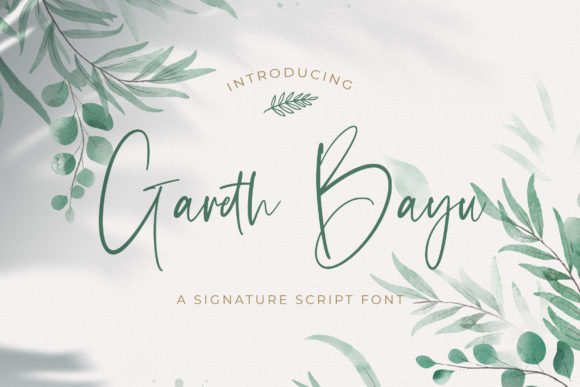
Gareth Bayu - это тонко начертанный, стильный и скорописный шрифт.
Он добавит роскошную искру в любой дизайнерский проект, который вы захотите создать!
Влюбитесь в его невероятно универсальный стиль и используйте его для создания эффектных дизайнов!